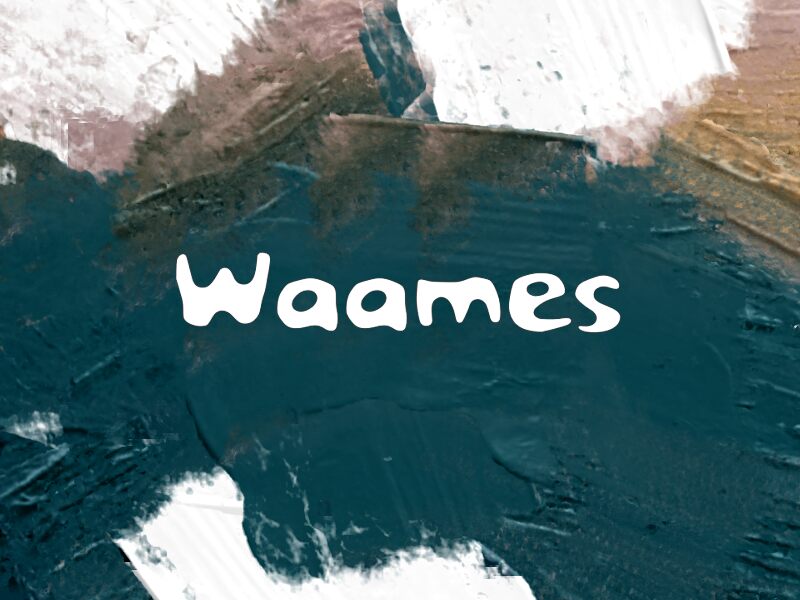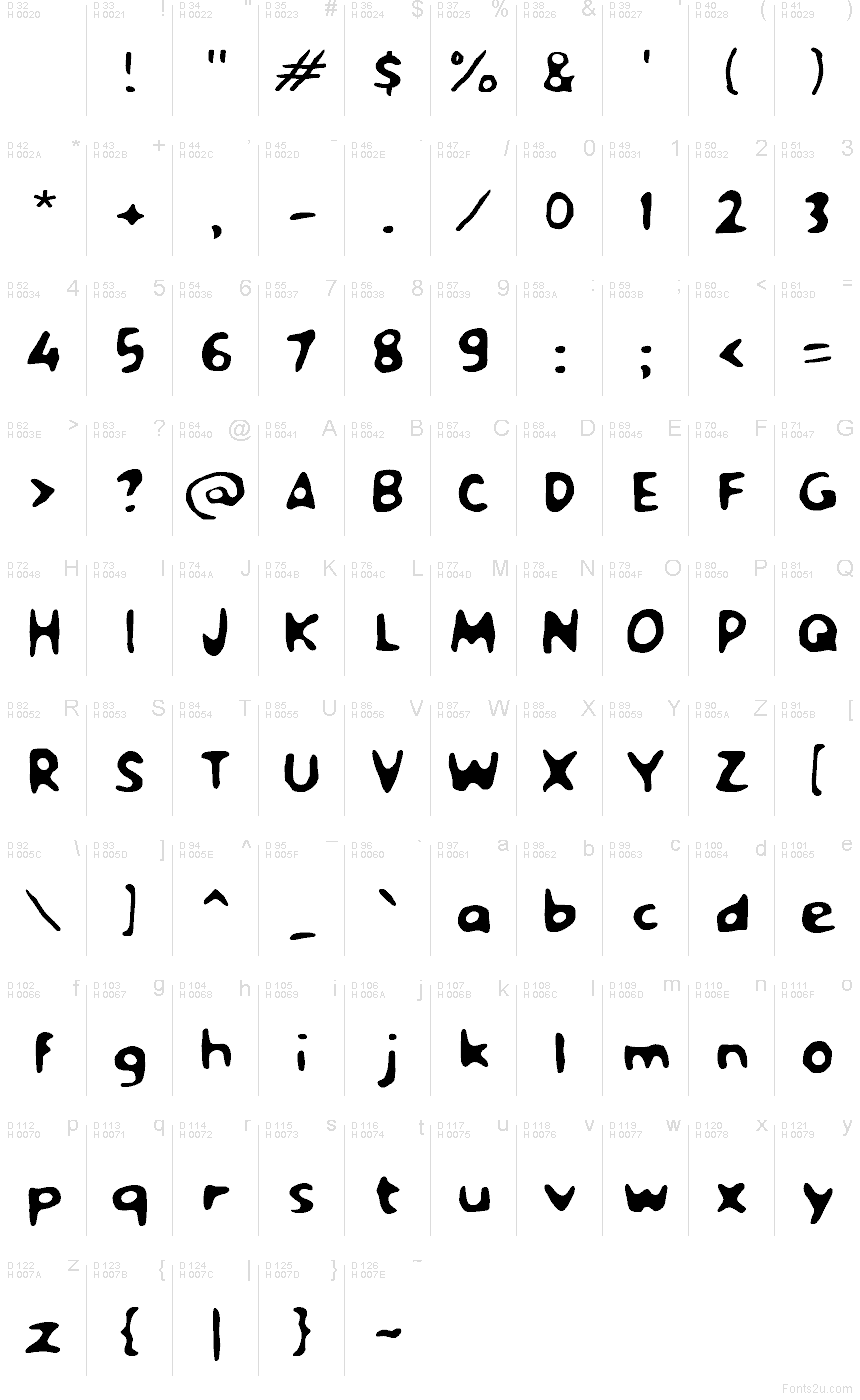
Waames
Waames de Wep es una tipografía display retro y orgánica, con un ritmo suave y fluido que resulta divertida desde la primera letra. Sus formas parecen más vertidas que dibujadas, con aperturas redondeadas, siluetas pesadas y una línea base ligeramente ondulada que le da a toda la fuente un aire desenfadado estilo cartoon.
Encaja perfectamente en titulares de pósters, branding infantil, arte musical, packaging y gráficos para redes sociales donde se necesiten palabras cortas con una presencia amigable y gomosa. Al ser una tipografía gratuita, Waames también funciona muy bien en tarjetas de título, citas destacadas y bocetos de logotipos, especialmente cuando buscas letras que se sientan moldeadas a mano y un poco fuera de lo común, en lugar de perfectamente pulidas.